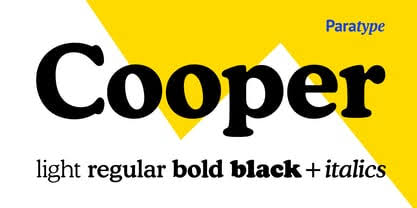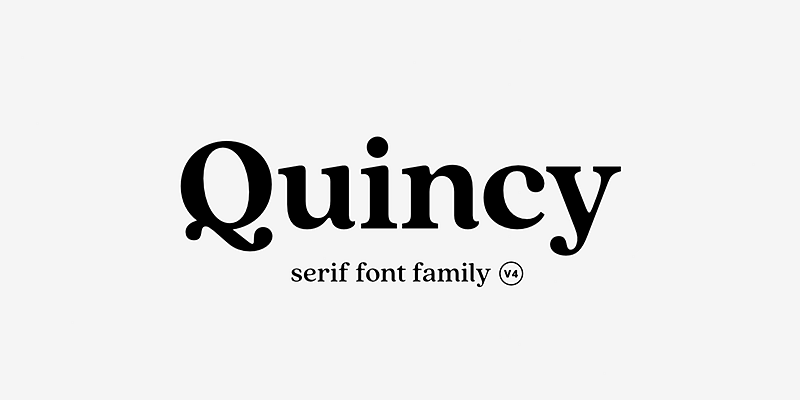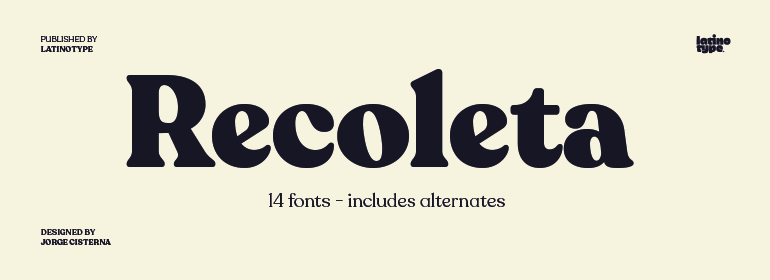
Rekomendasi Font Soft Serif untuk Desain Grafis
Desain logo dapat memiliki kombinasi warna yang menarik dengan memilih warna yang harmonis dan sesuai kebutuhan desain. Kombinasi warna dalam logo tentunya akan mengutamakan kesesuaian dengan identitas merek dan tampil menarik. Gaya font serif yang soft termasuk yang banyak dipilih untuk digunakan menciptakan desain grafis yang elegan, sederhana dan minimalis.
Font serif yang digunakan dalam desain memiliki banyak sekali gaya huruf yang bisa menciptakan kesan berbeda. Jenis font serif umumnya memiliki huruf dengan dekorasi serif, bentuk serif memiliki banyak jenis. Bentuk serif ini yang memengaruhi kesan yang diciptakan oleh font serif ada yang lembut, elegan dan ada yang bergaya formal.
CIRI FONT SOFT SERIF
Font serif pada umumnya memang akan memiliki bentuk huruf yang sederhana termasuk bentuk serifnya. Gaya huruf pada jenis font soft serif ini memiliki desain huruf yang lebih bersih, sederhana dan serif yang tidak panjang atau tebal. Ciri umum dari font soft serif ini seperti:
• Memiliki Gaya Huruf Modern
• Garis yang Lembut dan Sudut Melengkung
• Detail Huruf Elegan
• Serif Lancip dan Bulat
• Memiliki Variasi Huruf tebal yang Bulat
Penggunaan gaya huruf serif yang lembut bisa digunakan untuk menciptakan kesan brand yang elegan. Font lembut juga berguna memudahkan tipografi dibaca sehingga menyampaikan pesan dengan efektif.
REKOMENDASI FONT SOFT SERIF
Penggunaan font serif yang lembut dalam desain grafis bisa digunakan dalam berbagai jenis desain. Biasanya dipilih untuk memastikan tipografi mudah dibaca, tampil minimalis dan berkesan profesional. Berikut beberapa rekomendasi font soft serif yang elegan:
Quincy
Gaya font ini memiliki style huruf tipis sehingga bisa menciptakan desain yang elegan hingga kesan feminim. Serif dalam font tersebut memiliki ujung serif lancip dan pendek sehingga tidak mengganggu keterbacaan huruf. Beberapa ujung huruf berbentuk bulat dan melengkung, termasuk sudut yang terlihat melengkung sehingga berkesan ramah.
Penggunaan gaya font ini dalam desain brand akan tampil elegan dan mewah. Style desain harus minimalis dan bersih agar relevan dengan gaya huruf yang sederhana. Jenis font soft serif satu ini bisa digunakan untuk merepresentasikan jenis brand fashion hijab, parfum hingga skincare.
Cooper BT
Font soft serif kebanyakan memiliki visual yang lembut dari garis huruf yang tidak tajam tetapi bulat dan melengkung. Termasuk pada font Cooper yang memiliki serif dan bergaya bulat sehingga tampil lembut. Sudut dan ujung serif tidak lancip tetapi memiliki sudut melengkung yang ramah.
Font serif lembut ini juga memiliki gaya huruf yang lebih tebal sehingga memiliki keterbacaan yang lebih baik. Penggunaan font ini akan mudah menarik perhatian, tampil elegan dan ramah. Penggunaan yang cocok untuk jenis font tebal ini adalah untuk brand makanan atau brand minuman.
Recoleta
Font tipis atau regular dalam jenis font serif memiliki kemampuan menciptakan visual yang elegan dan mewah. Gaya huruf font ini juga bersih dan sederhana sehingga akan memiliki keterbacaan yang baik. Sudut font tampil lebih elegan dan halus, dengan ujung serif lancip yang pendek.
Meski gaya huruf elegan, namun font serif yang lembut tidak tampak kaku dan berkesan lembut. Garis huruf yang halus dan bersih memudahkan font untuk merepresentasikan desain minimalis yang mewah. Gunakan font tipis yang elegan untuk desain brand seperti fashion dan kecantikan.
The Youngest
Font lembut ini memiliki visual yang lebih elegan dibandingkan beberapa font tersebut, sehingga bisa menciptakan desain yang menarik. Gaya huruf ini akan lebih cocok merepresentasikan brand feminim dan elegan seperti fashion hijab dan kosmetik. Tipografi font yang sederhana juga memudahkan font untuk fleksibel dalam berbagai desain modern.
Bentuk serif yang lancip dan garis huruf yang elegan menciptakan kesan mewah, tetapi tidak terlihat kaku. Gaya huruf yang tipis akan menciptakan desain visual yang bersih dan sederhana. Font soft serif yang elegan ini akan relevan juga untuk brand fashion, parfum hingga skincare.
PENGGUNAAN DALAM DESAIN GRAFIS
Gaya huruf yang lembut biasanya tidak memiliki banyak sudut yang tajam, garis-garis melengkung banyak terlihat pada desain hurufnya. Selain itu sudut-sudut dalam huruf akan menciptakan kesan ramah dan bentuk huruf yang bulat. Dalam desain grafis penggunaan gaya font soft serif bisa digunakan untuk kebutuhan desain seperti:
Untuk Logo Elegan
Dalam desain logo penggunaan font serif yang sederhana ini akan efektif membantu nama merek mudah dibaca dan diingat. Selain memiliki keterbacaan yang baik, logo juga akan berguna menciptakan citra brand yang mewah dan elegan. Penggunaan font elegan akan berguna untuk menciptakan desain visual yang bersih dan minimalis.
Jenis font yang memiliki serif memiliki banyak gaya huruf seperti elegan, formal, tegas hingga feminim. Ketebalan huruf dan bentuk serif akan memengaruhi kesan yang diciptakan setiap jenis variasi font serif. Gaya font soft serif yang lembut bisa menciptakan desain grafis atau brand yang elegan, mewah dan profesional. Berbagai gaya font serif yang lembur bisa digunakan untuk merepresentasikan kesan tertentu dalam berbagai jenis brand dan desain.